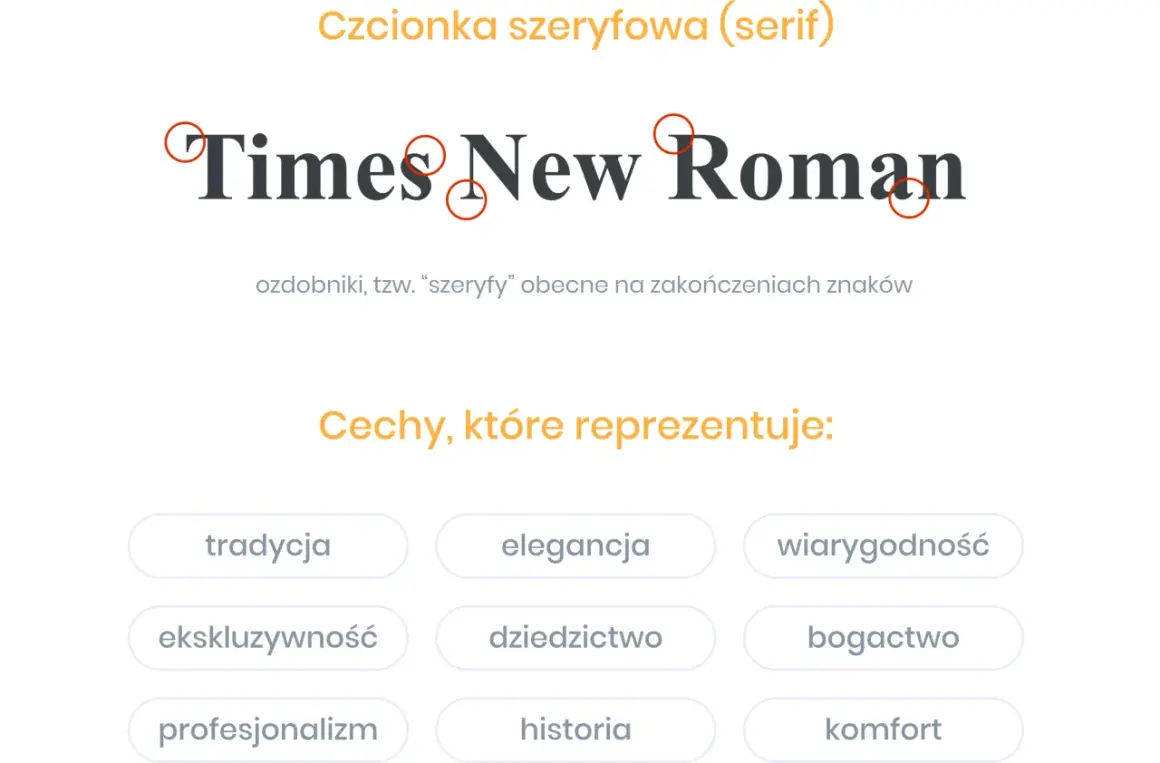
Font szeryfowy - Kiedy go używać i jak dobrać?
Czcionka szeryfowa Times New Roman, z widocznymi ozdobnikami, symbolizuje tradycję, elegancję i wiarygodność.
Dobry krój pisma potrafi zmienić odbiór całej publikacji szybciej niż układ zdjęć czy kolor tła. Font szeryfowy kojarzy się z elegancją, tradycją i spokojnym rytmem czytania, ale w praktyce nie chodzi wyłącznie o estetykę. W tym tekście pokazuję, czym są szeryfy, kiedy taki krój działa najlepiej, jak odróżnić go od bezszeryfowego odpowiednika i jakie błędy najczęściej psują efekt w druku oraz na ekranie.
Najważniejsze informacje w skrócie
• Szeryfy to drobne zakończenia liter, które wpływają na charakter i rytm tekstu, nie tylko na jego ozdobność.
• W długich materiałach drukowanych dobrze dobrany krój szeryfowy często daje bardzo komfortowe czytanie.
• O efekcie decydują też interlinia, kontrast, długość wiersza i rodzaj papieru.
• W projektach fotograficznych, albumach i materiałach premium szeryfy pomagają zbudować bardziej klasyczny ton.
• Na ekranach mobilnych oraz w małych podpisach częściej wygrywa prostsza, bezszeryfowa forma.
Czym wyróżnia się krój z szeryfami
Szeryfy to krótkie, często delikatne zakończenia na końcach linii tworzących literę. W praktyce nadają znakowi większą strukturę i sprawiają, że cały blok tekstu wygląda bardziej rytmicznie. W typografii ten styl krojów często określa się jako antykwę, czyli rodzinę opartą na klasycznych proporcjach liter, znaną z książek, czasopism i eleganckich druków.
Nie traktuję ich jako zwykłej dekoracji. Dobrze zaprojektowane szeryfy prowadzą oko po wierszu, porządkują tekst i budują ton publikacji. Gdy są zbyt ciężkie albo zbyt cienkie, efekt się odwraca, dlatego sama obecność szeryfów nie gwarantuje dobrego rezultatu.
Garamond, Baskerville, Georgia czy Times New Roman pokazują, jak szeroko można interpretować ten styl, od bardzo klasycznego po bardziej neutralny. To ważne rozróżnienie, bo w projektowaniu liczy się nie tylko sam typ liter, ale też ich zachowanie w konkretnym rozmiarze i na konkretnym nośniku.
Gdy już widać, jak działa ta grupa krojów, łatwiej ocenić, gdzie naprawdę daje przewagę.
Gdzie sprawdza się najlepiej w praktyce
W praktyce najlepiej działają tam, gdzie tekst ma być czytany dłużej, a nie tylko skanowany wzrokiem. Albumy fotograficzne, książki, katalogi, magazyny, zaproszenia, certyfikaty i eleganckie foldery to naturalne środowisko dla szeryfowych krojów. W materiałach związanych z fotografią szczególnie dobrze wypadają wtedy, gdy zdjęcia potrzebują spokojnego, redakcyjnego tła, a typografia ma nie walczyć z obrazem.
Ja zwykle patrzę na to prosto: jeśli projekt ma mówić „przemyślane, klasyczne, dopracowane”, taki krój jest dobrym kandydatem. Jeśli ma być dynamiczny, lekki i maksymalnie użytkowy, często lepiej zostawić go na nagłówki albo wyróżnienia, a tekst główny oprzeć na prostszej rodzinie.
Warto też pamiętać, że nie każdy szeryfowy krój pisma jest taki sam. Część ma bardziej historyczny charakter, część jest neutralna, a część jest wręcz zaprojektowana pod ekran. To dlatego nazwa rodziny mówi więcej niż sam ogólny typ.
Takie rozróżnienie prowadzi już wprost do pytania, kiedy lepiej postawić na styl szeryfowy, a kiedy wygodniej wybrać prostszy odpowiednik.
Szeryfowy czy bezszeryfowy w praktyce
Nie ma jednej reguły, która zawsze każe wybrać jedną stronę. Badania i praktyka projektowa pokazują raczej, że o czytelności decydują przede wszystkim wielkość, kontrast, długość wiersza i interlinia, a dopiero potem sam typ kroju. Dlatego przy wyborze porównuję sytuację użycia, a nie samą etykietę „szeryfowy” albo „bezszeryfowy”.
Sytuacja Lepszy wybór Dlaczego
Długi tekst w druku Szeryfowy krój pisma Buduje spokojniejszy rytm czytania i dobrze wygląda w blokach tekstu.
Interfejs, strona mobilna, małe podpisy Bezszeryfowy Prostsze kształty są czytelniejsze przy małych rozmiarach i gorszym podglądzie.
Album fotograficzny lub magazyn premium Szeryfowy albo mieszany układ Szeryfy dają bardziej redakcyjny, dopracowany charakter.
Krótki nagłówek na zdjęciu Zależy od tła i stylu Tu liczy się kontrast, ekspresja i ilość miejsca, nie sam typ kroju.
Materiał edukacyjny lub instrukcja Najczęściej bezszeryfowy Minimalizuje ryzyko zlewania się drobnych detali przy szybkim skanowaniu.
Jeśli nadal wahasz się między tymi dwiema rodzinami, zwykle warto zacząć od treści, a dopiero potem dobierać styl liter. Gdy jasny jest charakter materiału, łatwiej ustalić, jakim narzędziem go wzmocnić.
Jak dobrać odpowiedni krój do projektu
W dobrze zaprojektowanym składzie nie wybieram kroju „na oko”. Najpierw sprawdzam nośnik, długość tekstu i sposób, w jaki odbiorca będzie obcował z publikacją. Dla dłuższych bloków drukowanych bezpieczny punkt startu to zwykle 9,5-11,5 pt, interlinia 120-145% i wiersz mieszczący około 45-75 znaków. To nie jest żelazna reguła, tylko praktyczny zakres, który najczęściej daje czytelny efekt.